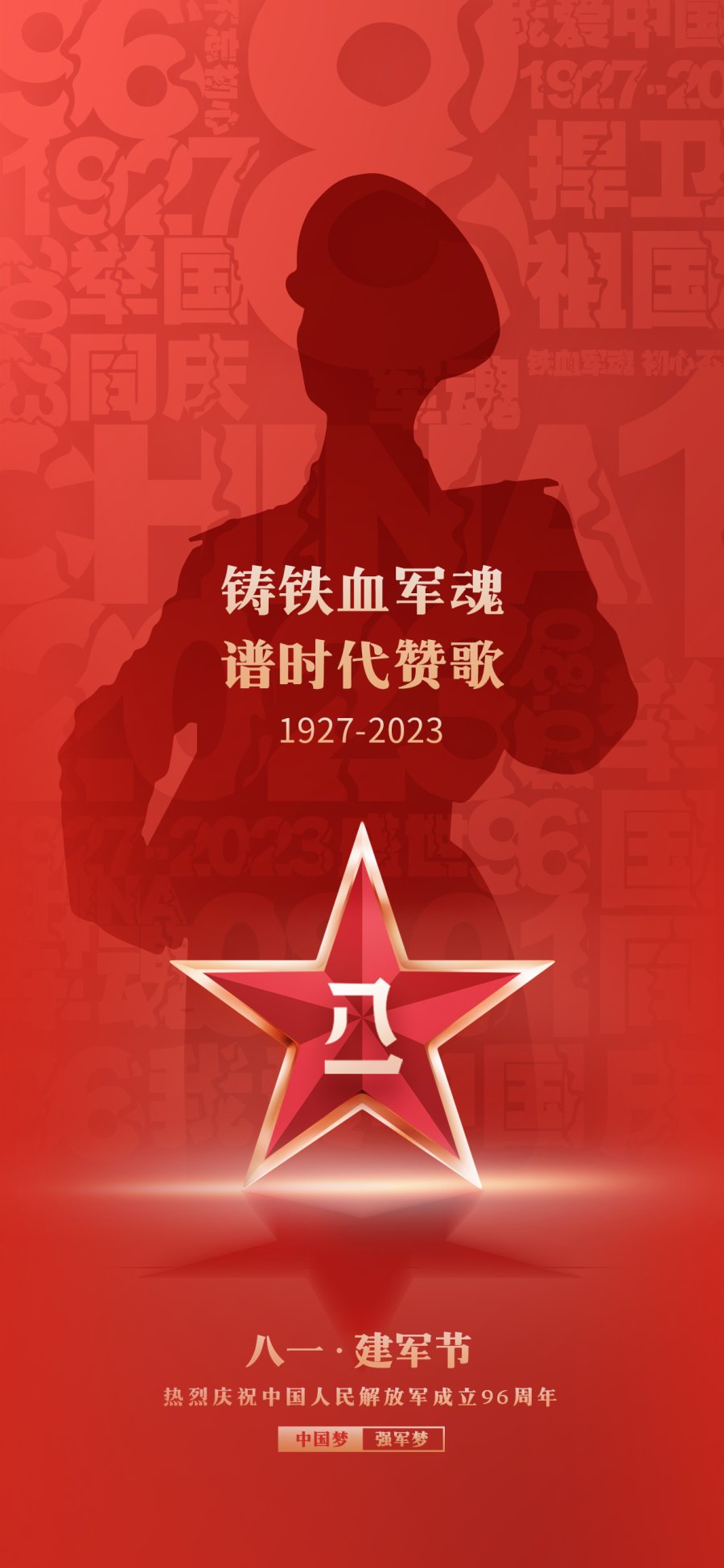
八一建军节,致敬英雄!
八一建军节,致敬英雄!铁血柔情,守护家国;军旅生涯,无悔选择。
展示字体一:印品霹雳体
印品霹雳体是一款稳重但又富有创意的字体,笔画之间生动变化,刻画出"列缺霹雳 丘峦崩摧"的震撼感。
展示字体二:印品雅宋简
印品雅宋简字体线条流畅顺滑,棱角柔滑,端正大气,装饰角的圆滑处理,使整个字浑厚有力十分耐看。